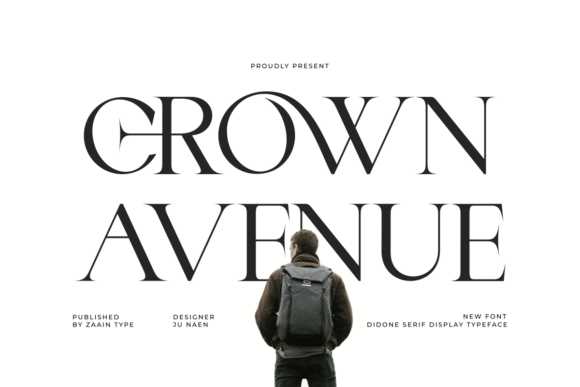
Crown Avenue
適切なデザイン要素を見つけるのは難しい場合がありますが、Crown Avenueは作品を即座に引き立てる優れたコレクションを提供します。
POD(オンデマンド印刷)製品、結婚式の招待状、またはソーシャルメディアのグラフィックを作成している場合でも、Crown Avenueは理想的です。